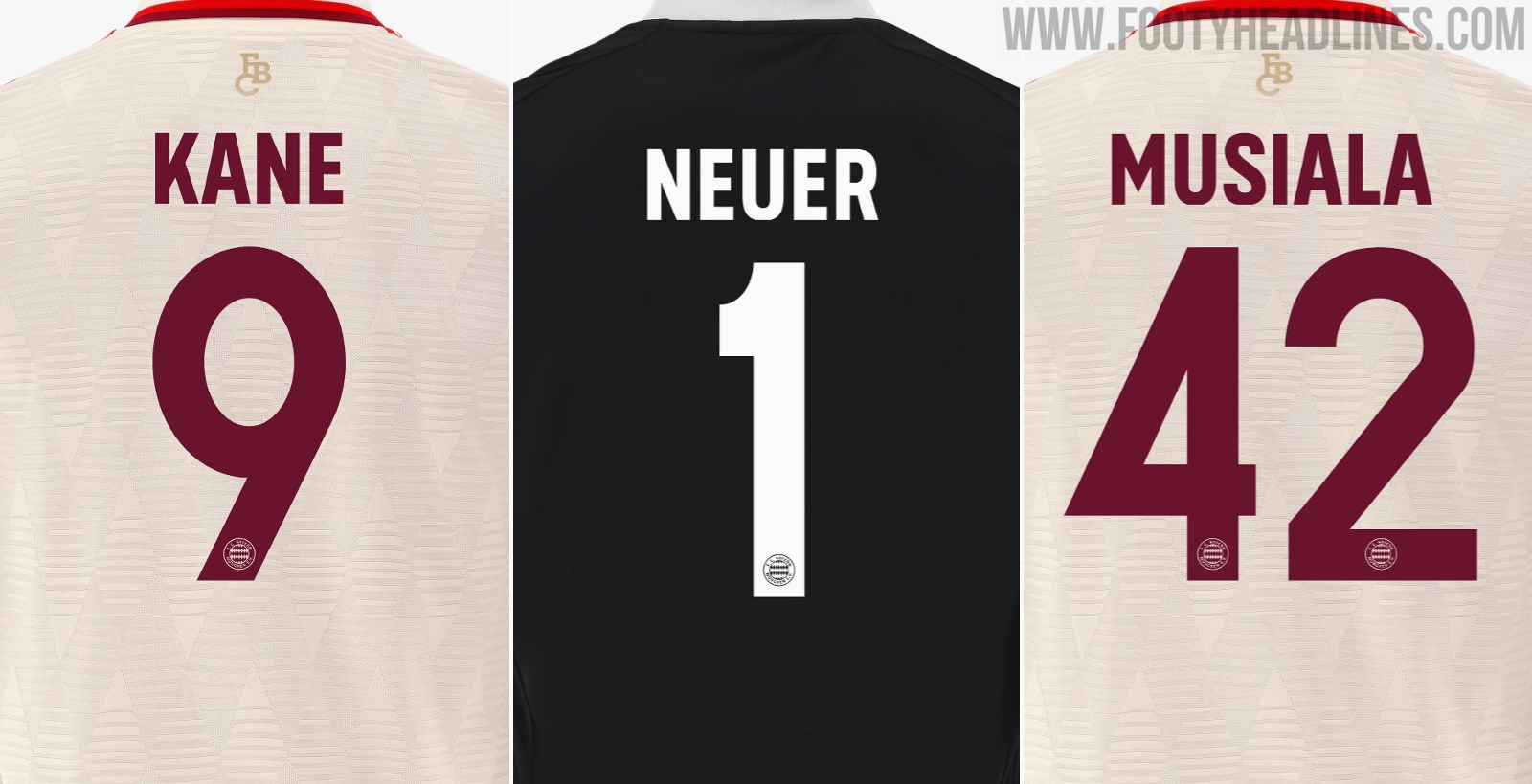
Rilasciato il font per la terza maglia del Bayern München 24-25 "Champions League
• Nuovo Font Champions League: Il Bayern Monaco ha rilasciato un font speciale per la maglia della UEFA Champions League 2024-25, che sarà utilizzato anche come terza maglia.
• Design Classico: Il nuovo font UCL presenta un aspetto decisamente classico, che si integra con il design tradizionale della maglia del Bayern.
• Dettagli Aggiuntivi: La versione monocromatica dello stemma retrò del Bayern è posizionata nella parte inferiore dei numeri, accentuando l'estetica vintage della maglia, e il font UCL costa 15 euro in più.
Il Bayern Monaco ha introdotto in sordina un font speciale per la sua maglia della UEFA Champions League 2024-25, che sarà utilizzata anche come terza maglia.
Font per la maglia del Bayern Monaco per la Champions League 24-25 e la terza maglia
Il font del Bayern Monaco 24-25 Champions League/Third Kit si distingue dal carattere tipografico utilizzato per le seconde maglie, basato su quello della Coppa del Mondo 2022 e rilasciato per la precedente stagione 2023-24.
Font Bayern Monaco 24-25 Regular vs Special Third
Questo nuovo carattere UCL ha un aspetto decisamente classico, che si integra con il design tradizionale della maglia del Bayern.
Un'ulteriore caratteristica è la versione monocromatica dello stemma retrò del Bayern, posizionato nella parte inferiore dei numeri, che enfatizza ulteriormente l'estetica vintage della maglia.
Terza maglia del Bayern Monaco 24-25 - Versione con font Bundesliga e nome della squadra
Il nome della squadra non è presente in Champions League. Per le partite della Bundesliga, il nome della squadra viene aggiunto in alto, mentre il nome del giocatore si sposta in basso. Questa versione non è disponibile per l'acquisto online.